모리사와 특별 강연, ‘서체 디자이너의 전망’
지난 7월 2일, 도쿄 아키하바라에서 이루어졌던 모리사와 특별 강연 내용을 정리해 소개한다. 가장 먼저, 50여 년간 서체 디자인 분야 선두에 있었던 매튜 카터(Matthew Carter)가 활자 시대의 몇몇 서체에 대해 슬라이드로 발표를 시작했다.
라틴 텍스트와 본문용 서체, 매튜 카터
지난 7월 2일, 도쿄 아키하바라에서 이루어졌던 모리사와 특별 강연 내용을 정리해 소개한다. 가장 먼저, 50여 년간 서체 디자인 분야 선두에 있었던 매튜 카터(Matthew Carter)가 활자 시대의 몇몇 서체에 대해 슬라이드로 발표를 시작했다. 매튜 카터는 타이포그래피 기술이 활자 인쇄에서 사진 식자, 그리고 디지털 조판까지 진화해 오는 동안 오랜 시간 그 선두를 지켜온 인물이다.
그는 옛 스크립트 서체들이 과거에 긴 본문을 위해 어떻게 쓰였는지, 그리고 지금은 더 이상 이 목적을 위해 쓰이지 않는다는 것에 대해 설명했다. 비슷한 맥락으로 예전에는 블랙 레터(blackletter) 서체들이 읽기 쉬웠고 모두 읽을 수 있었지만, 요즘에는 사람들이 계속 이어지는 본문에서 더 이상 블랙 레터를 읽는 습관이 되어 있지 않다고 덧붙였다.
<New York Times>와 <International Herald Tribune> 제호 슬라이드들을 보여주면서, 그는 블랙 레터가 신문 제호로 선택되는 것은 흥미로운 전통이라고 지적했다. 또한 다른 서체들을 보여주면서, 그 서체들 중 몇몇은 한때 본문에서 읽기 쉬웠지만 사람들이 그것을 읽는 습관을 잃어서 지금은 포스터에서 커다란 크기로 쓰이는 것에 제한되었다고 설명했다.
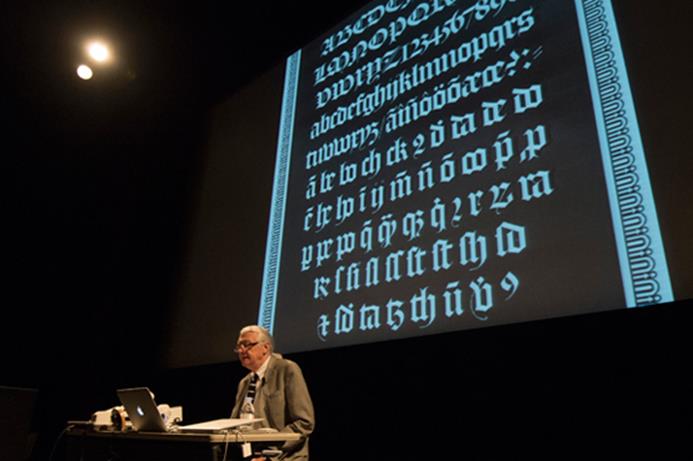
그리고 매튜 카터는 그가 디자인한 서체 중 몇 개를 보여주었다. 그 중 ‘밀러(Miller)’ 서체 패밀리는 타블로이드와 일반적인 신문에 쓰이도록 다양한 버전을 갖추고 있다. 한 신문사 고객을 위해 그는 웨이트(weight, 굵기)에서 단지 약간의 퍼센트 차이가 나는 서로 다른 버전들을 준비했다고 설명했다. 그는 사용된 인쇄 기술(사용된 잉크의 양), 또는 일러스트레이션에 할당된 페이지 공간의 양에 따라 다른 웨이트를 사용하는 예들을 보여주었다.
처음에 잡지 <Newsweek>를 위해 매튜 카터는 본문, 작은 표제, 큰 표제를 위한 세 가지 서체의 버전을 디자인해 달라는 의뢰를 받았다. 후에 그는 신문의 톱 전단에 걸친 제목(큰 헤드라인)을 위한 네 번째 버전과 그 보다 두꺼운 웨이트를 가지거나, 반전된 서체(어두운 배경에 쓰인 밝은 글자)를 위한 다른 버전들에 대한 제작을 요청 받았다고 설명했다.
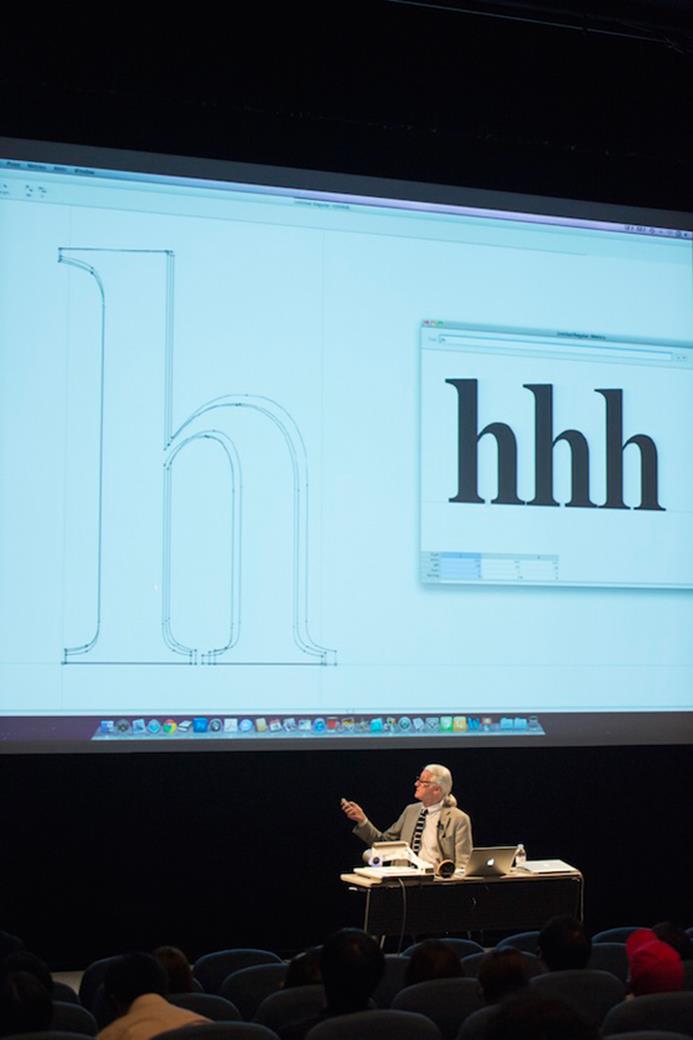
매튜 카터는 디지털화에 대한 주제로 넘어가며 ‘몬티첼로(Monticello)’라는 서체를 예로 들었다. 그는 활자에 내재된 기술적인 한계 때문에 그 글립들 중 몇 개는 문제를 가지고 있었다고 말했다. 그는 새로운 디지털 버전을 만들어 달라는 요청을 받고 서체가 보다 우아하게 보이도록 다시 디자인했다.
활자에서 디지털로 넘어갈 때 서체를 바꾸는 다른 예들을 보여주면서, 그는 서체가 활자(metal)에서 아무리 좋았다고 하더라도 그것을 디지털 버전으로 만들거나 단순히 활자에서의 이미지를 스캔하여 그대로 디지털화할 경우 제대로 기능하도록 하는 일은 어렵다고 강조했다. 많은 예시를 보여주며 논리적으로 설명해준 매튜 카터의 발표는 통찰로 가득했다. 서체 디자이너들뿐만 아니라 서체를 사용하는 다른 디자이너들에게도 도움될 내용이 많았다.
‘와란’ 디자인, 쿠니히코 오카노
‘와란(Waran)’은 2012년 모리사와 서체 디자인 공모전(Morisawa Type Design Competition 2012,http://competition.morisawa.co.jp) 간지(일본어 한자) 부문에서 금메달을 받은 서체다. ‘와란’을 디자인한 쿠니히코 오카노(Kunihiko Okano)는 그가 어떻게 서체 디자인에 흥미를 느끼게 되었는지, 그리고 ‘와란’을 만드는 과정에 대한 이야기를 들려주었다.
오카노는 대학에서 그래픽 디자인을 공부하면서 서체 디자인에 처음으로 이끌렸다고 회상했다. 포스터를 만드는 학과 과제를 받았을 때 그는 목적에 맞는 서체를 찾는데 어려움을 느꼈고 그 계기를 통해 스스로 서체를 디자인해보자는 생각을 하게 되었다고 한다. 후에 그는 서체 디자이너가 되도록 영감을 주고 동기를 부여한 매튜 카터의 소피아(Sophia)를 만났다.
그리고 ‘와란’을 디자인하게 된 계기는 그가 네덜란드에서 서체 디자인을 공부할 때 찾아왔다. 에셔 박물관(Escher in Het Paleis, www.escherinhetpaleis.nl)와 마우리츠후이스 왕립 미술관(Royal Picture Gallery Mauritshuis, www.mauritshuis.nl) 등과 같은 박물관들은 시각적인 부분의 일관성을 부여하기 위해 표지판, 팜플렛, 그리고 다른 요소들을 위해 주문 제작한 서체를 갖고 있었다.
그런데 그런 디자인 요소들의 일본어 버전은 서체를 제대로 선택하지 못해 일관된 이미지를 형성하는데 실패한 것으로 보였다. 그것이 오카노로 하여금 일본어와 서구 글자들 사이에 일관성 있는 표정을 갖는 서체 디자인에 대해 고민하도록 만들어주었다. 외국 기업들이 그들의 라틴 서체에 잘 맞는 일본 서체를 필요로 한다는 점을 알고 오카노는 완전히 새로운 개념으로 일본 서체를 만들기로 결심했던 것이다.
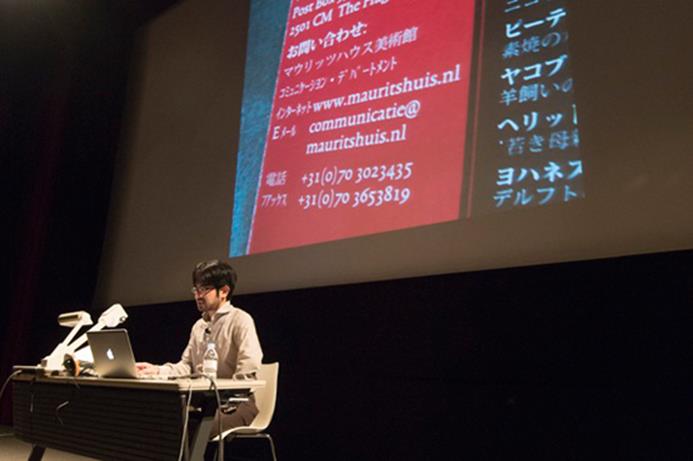
‘와란’을 디자인할 때 오카노는 라틴 서체가 보다 중심적인 역할을 하면서 일본어와 라틴 글자 모두에 동일한 디자인 컨셉을 갖는다는 것을 목표로 했다. 일본의 지배적인 트렌드와는 반대로, 그는 라틴 서체가 일본 글자들의 보조적인 역할을 하는 것을 원하지 않았고, 필요하다면 라틴 글자들에 맞도록 일본 글자들을 조정하기로 결정했다. 그는 전에 만들었던 실험적인 디자인에 기반해 라틴 서체를 그리고 라틴 서체에 맞도록 일본 서체를 처음부터 디자인했다. 그 결과물이 모리사와 서체 디자인 공모전에 출품한 와란이다.
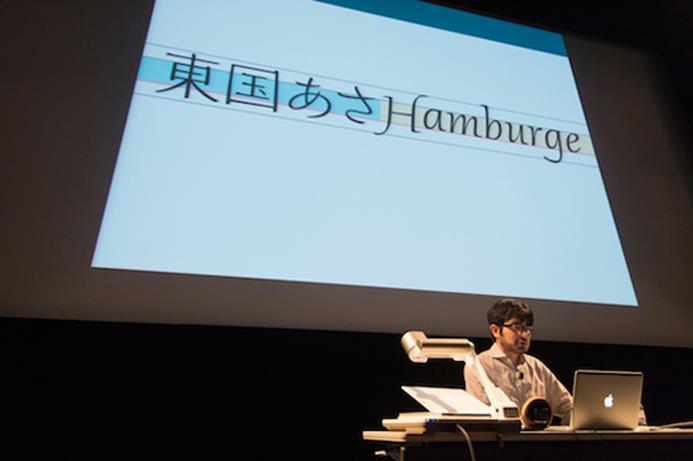
‘와란’을 디자인하는데 있어서, 그는 글자들의 허리 위치에 집중했다. 그는 처음에 라틴 알파벳에서 소문자들만 허리 부분을 올리려고 했는데, 이것은 라틴 글자들이 일본 글자들에 보조적인 역할만 하도록 하는 결과를 가져왔다. 그리고 일본 글자들의 허리선을 낮고 아래쪽으로 갈수록 약간 넓어지도록 그렸다. 전체적으로 ‘와란’은 수평 획들을 의도적으로 평평하게 정렬하고 수직 획들을 자유롭게 흐르도록 함으로써 수평적인 조판의 적합성을 강조했다. 명조나 산세리프 서체에 속하지 않는 새로운 일본 서체를 만들기 위해 그는 수평 선들의 오른쪽 가장자리가 강조되는 전통적인 일본 서체와는 달리 수평 획의 왼쪽 가장자리에 강조점을 두었다.
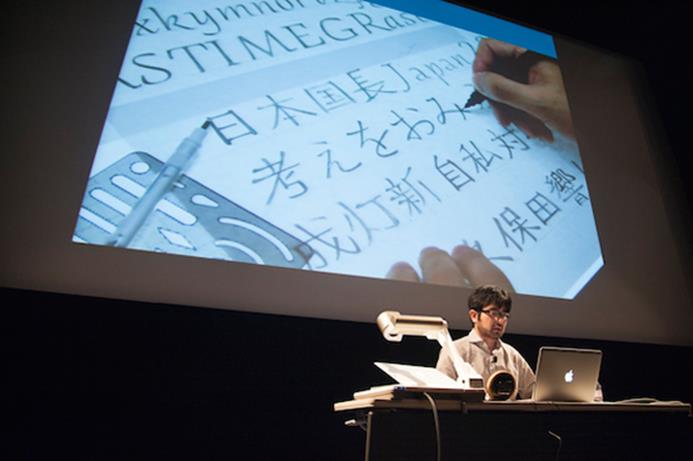
오카노는 손으로 그린 스케치와 제작 자료에 대한 슬라이드를 보여주면서 최초의 디자인이 제작 과정에서 어떻게 발전했는지 설명하고, 사진과의 조화 가능성을 시험해보기 위해 가짜 광고물을 사용하여 그가 만들었던 모의 작업들을 보여주었다. 그의 발표는 ‘와란’을 디자인하는 것이 얼마나 길고 힘든 여정이었는지 잘 보여주었다. 오카노는 ‘와란’으로 공모전에서 금메달을 받고 다시 일본 서체 디자인을 공부하고 있다. 그의 발표 끝 부분에서, 그는 10년 안에 일본어와 라틴 서체의 조합으로서의 ‘와란’을 발매하는 것이라고 다음 목표를 밝혔다.
히라가나에 대한 나의 생각. 마사히코 코즈카
세미나 마지막 발표자는 1950년부터 실무에 몸담아 온 서체 디자인 디렉터, 마사히코 코즈카(Masahiko Kozuka)였다. 히라가나에 대한 그의 강의는 1960년대와 1970년대 새로운 일본 서체 디자인 붐의 선봉이었던 ‘타이포스(Typos)’ 슬라이드로 시작되었다. 그는 타이포스 디자이너들 중 한 명인 야사부로 쿠와야마(Yasaburo Kuwayama)가 처음으로 타이포스를 라틴 알파벳처럼 가나 서체 패밀리로 상상했다고 지적했다.
그때까지는, 대부분 간지와 가나는 하나의 통합된 전체로 생각해야 하고 따로 고려해서는 안 된다고 생각되었다. 코즈카는 명조 간지와 가나가 한 단일체의 두 부분이라는 것이 당연하게 여겨졌던 그 시대에 가나를 간지로부터 독립적인 것으로 본 것은 혁명적인 생각이었다고 설명했다. 또한 새로운 서체의 다른 중요성은 글자를 개발하는 데 있어 패턴을 만든 것이었다고 지적했다.
타이포스에서 각 히라가나는 그것을 구성하는 요소들로 쪼개져 패턴을 만든다. 이것은 활자에선 불가능했다. 그는 간지 ‘波’에서 나온 히라가나 ‘は’의 예를 들었다. 그는 그 시대에 ‘は’를 세로획, 가로획 그리고 끝의 둥글게 휘어진 획 같은 다른 부분들의 모음으로 보는 것은 혁명적이었다고 말했다.
그러나 동시에 그는 가나의 부분들을 모듈화하는 것이 적합한지 의문을 던졌다. 그는 모듈화는 제목용 서체에만 국한해야 한다고 생각하고, 대신 본문에 쓰일 가나를 어떻게 다뤄야 하는가에 초점을 맞추었다.
일본어로 글을 쓸 때 사람들은 왼쪽에서 오른쪽으로 쓴다. 그러나 일본 책은 수직과 수평 조판을 가지고 있다. 히라가나는 원래 수직 조판을 위해 개발되었으므로, 그것을 수평 조판을 위해 옆으로 단순히 나열하는 것은 충분하지 않다. 그는 지금까지 아주 적은 서체들만 히라가나를 수평으로 쓰는 것을 위해 개발하는 도전을 해결했다고 강조했다.
코즈카는 그의 디자인 컨셉인 (1) 웨이트, (2) 허리 위치, (3) 속공간, (4) 요소들의 형태와 특징, (5) 선의 품질에 대해서도 설명했다. 이에 근거하여 그는 손글씨를 사용해 구체적으로 설명을 이어갔다. 히라가나 ‘は’를 예로 들었다. 이 글자의 근원은 간지 ‘波’이기 때문에 왼쪽의 세로획은 물 수 변(氵)에서 온다. 반면, 히라가나 ‘ほ’는 간지 ‘保’에서 온다.
이것은 왼쪽 세로획이 사람 인 변(亻)을 나타낸다는 것을 의미한다. 그는 이 부수들이 같은 형태를 가지는 것이 적합한지 의문을 가져봐야 한다고 말한다. 이를 고려하여 그는 많은 예들을 제시하며 현대에 수평 조판을 위해 간지에서 나온 히라가나를 다시 디자인할 때 생각해야 할 점들을 위에서 언급한 디자인 요소들에 초점을 맞추어 설명했다.
코즈카는 다음과 같이 서체의 기능을 정의하며 발표를 마무리했다.
(1) 정렬된 선들을 만드는 것
(2) 정보를 정확하게 전달하는 것
(3) 시각적인 이미지를 표현하는 것
그는 글자를 사용하는 그래픽, 편집 디자이너들이 서체를 고를 때에 필요에 따라 이 부분들을 기억하고 그 지점으로 되돌아가보는 것이 중요하다고 강조했다.